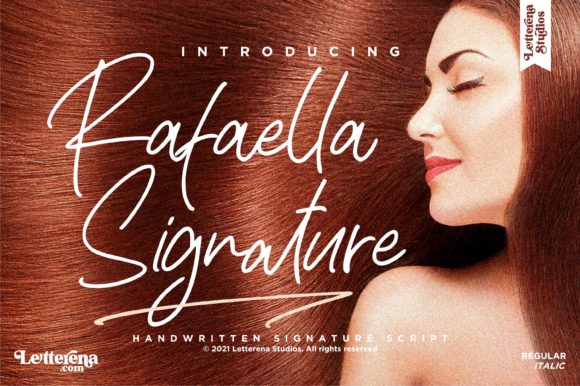
Creativefabrica Rafaella Signature Font
[Creativefabrica] Rafaella Signature Fontъ
Rafaella Signature - это изысканный рукописный шрифт, мастерски созданный, чтобы стать настоящим фаворитом. Он сохраняет свои стильные каллиграфические влияния и в то же время чувствует себя современным и свежим. Влюбитесь в него и поднимите свои проекты на самый высокий уровень!